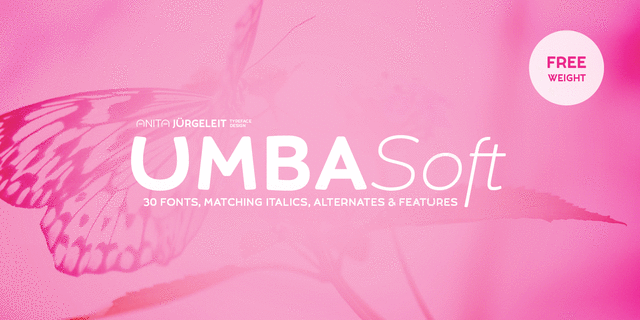
UMBA Soft – это мягкий гротеск со скругленными краями, успокаивающий ваш дизайн, и помогающий сбалансировать текст и изображения. Вам нужен шрифт для подростковой косметики или других продуктов, связанных с молодыми людьми? Ваше творение должно быть мягким и нежным и вам нужен соответствующий шрифт? Что-то приятное, сладкое, мягкое, но с широкими возможностями серьезного шрифтового семейства, решающего различные задачи? Umba Soft – ваш выбор! Ваша типографика значительно улучшится и UMBA Soft станет вашим любимым шрифтом!
Тридцать начертаний с насыщенностями от тонкого до жирного, плюс соответствующие курсивы, помогут вам создать очень привлекательный дизайн. Альтернативные формы знаков и капитель доступны в виде наборов начертаний. Для их использования не требуются специальные программы. Начертания появятся в меню выбора шрифта, чтобы вы всегда видели возможности новой гарнитуры.
Шрифт разработала Анита Юргелайт в 2019 году.
Ассоциации c начертанием UMBA Soft SC ThinКачества и характер:
деликатный, чистый, легкий, прохладный, холодный, тонкий, современный, ровный, качественный, модный, гибкий, самобытный, оригинальный, городской, неоновый, ясный, проволочный, свежий, лаконичный, понятный, вкусный, невесомый, прозрачный, интимный, хрупкий, нежный, воздушный, худой